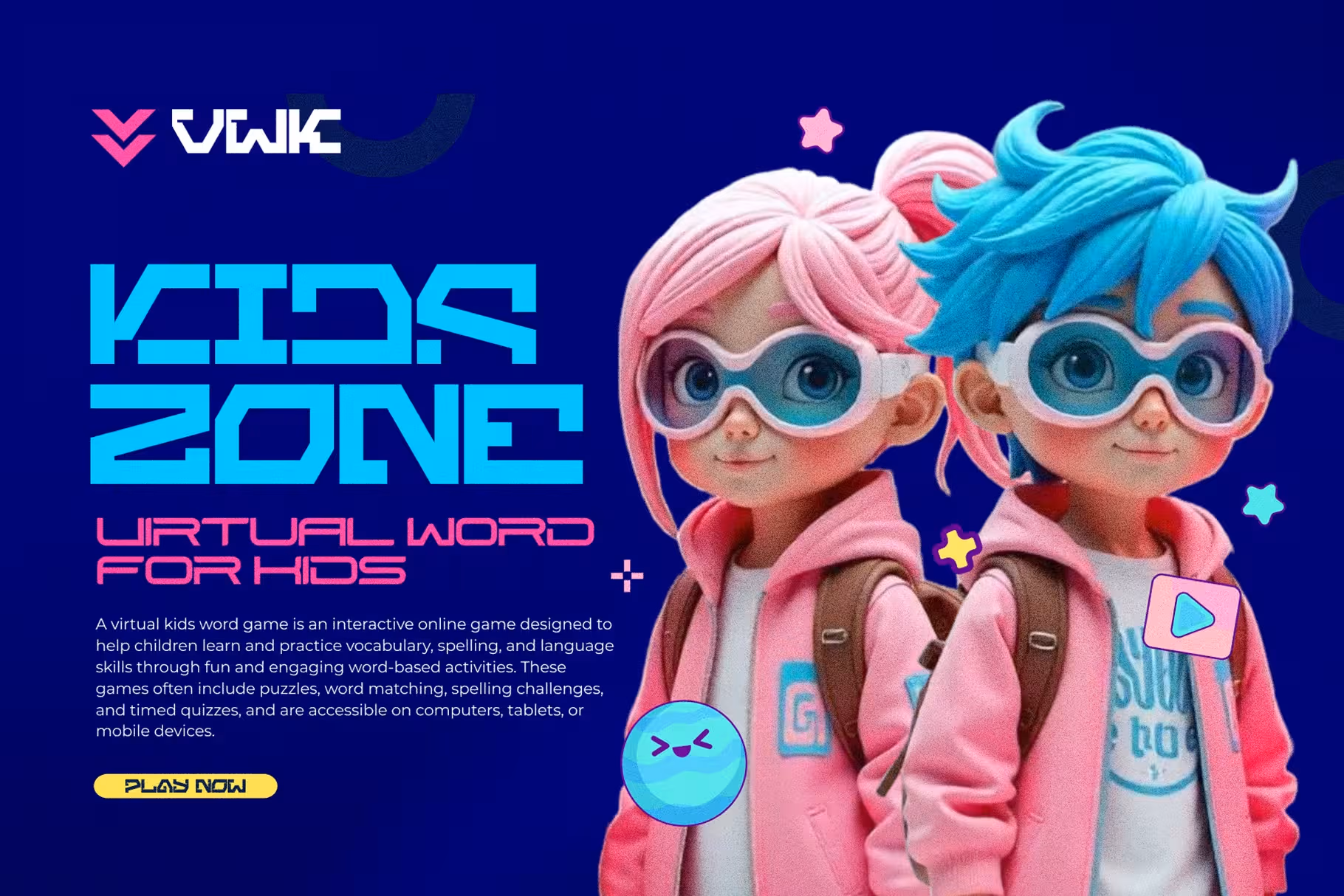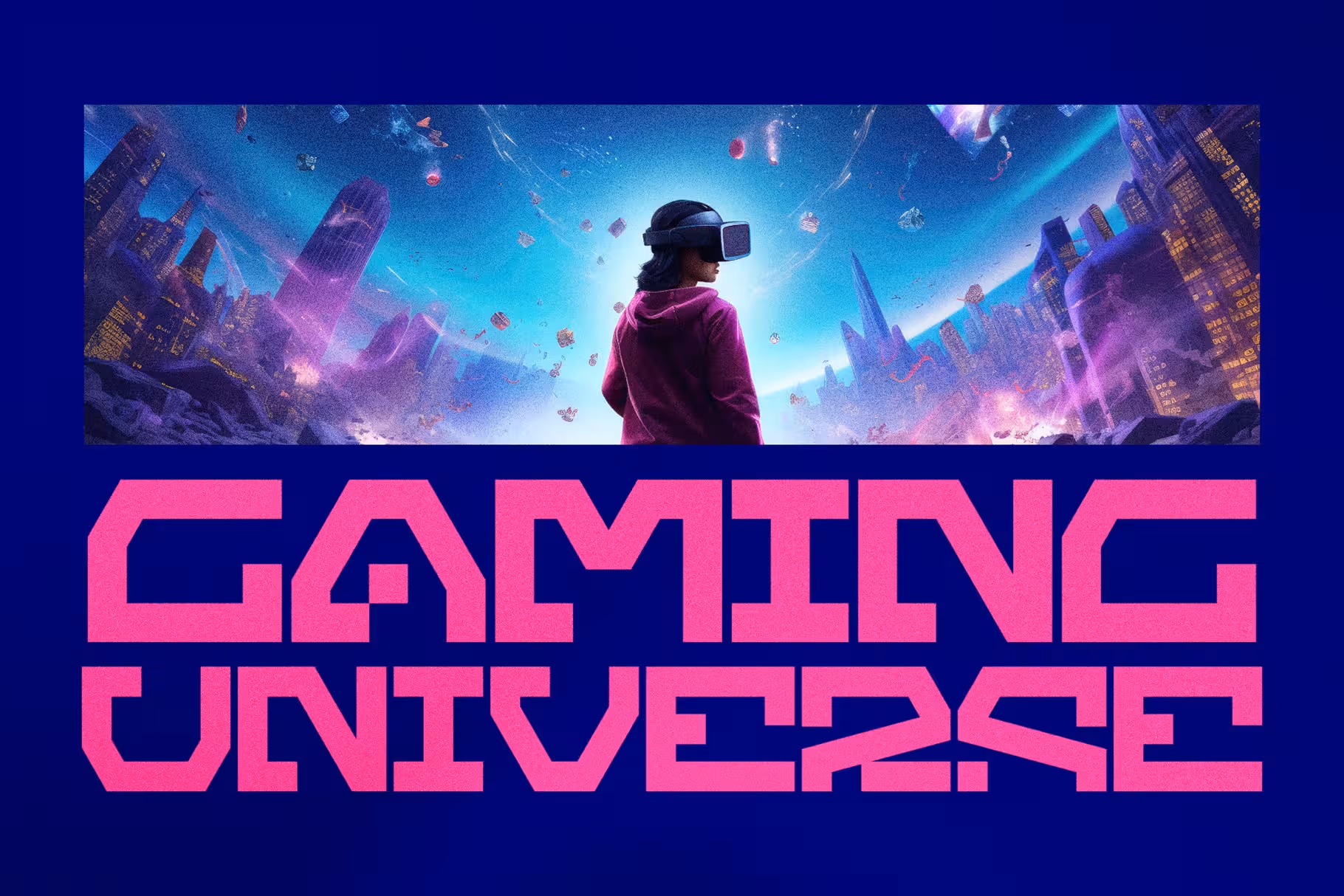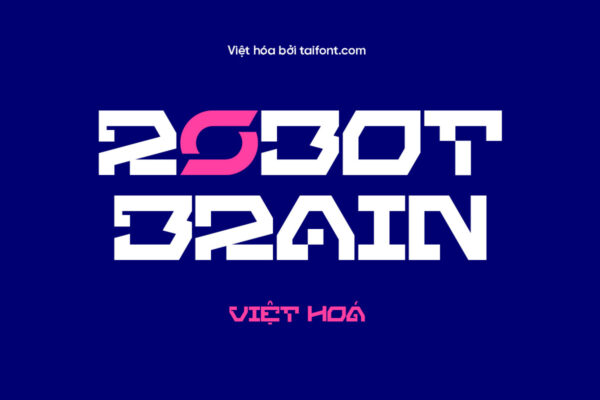
Giới thiệu về Font TF Robot Brain Việt hóa
TF Robot Brain Việt hóa là một font chữ trang trí độc đáo, nổi bật với thiết kế hiện đại, sắc nét và đầy tính công nghệ, gợi cảm giác về những mạch điện tử, mã code hoặc các yếu tố của trí tuệ nhân tạo. Font này toát lên phong thái tương lai, mạnh mẽ và đầy ấn tượng, lý tưởng để tạo điểm nhấn độc đáo và thu hút mọi ánh nhìn trong các thiết kế đòi hỏi sự tiên tiến và phong cách khoa học viễn tưởng.
Với đặc điểm thiết kế độc đáo, góc cạnh mạnh mẽ và khả năng gợi cảm xúc về công nghệ, Robot Brain là lựa chọn hoàn hảo cho các ấn phẩm trong lĩnh vực giải trí, công nghệ và tương lai:
- Thiết kế game: Hoàn hảo để sử dụng cho logo game, tiêu đề, hoặc các ấn phẩm quảng bá các tựa game khoa học viễn tưởng, game hành động, game chiến thuật hoặc game có chủ đề robot, AI. Font này giúp tạo không khí kịch tính, lôi cuốn và đầy thách thức, làm nổi bật tên game hoặc các tiêu đề quan trọng, khiến game thủ cảm thấy hào hứng và muốn khám phá.
- Công nghệ game: Lý tưởng để sử dụng trong các giao diện người dùng (UI) của game, màn hình tải game, hoặc các yếu tố đồ họa liên quan đến công nghệ, hệ thống AI trong game. Nét chữ sắc sảo của font sẽ làm tăng tính chân thực và độ “ngầu” cho trò chơi.
- Poster game: Phù hợp cho các poster quảng bá game, banner sự kiện E-sport, hoặc các ấn phẩm truyền thông liên quan đến công nghệ game. Font này giúp tạo không khí mạnh mẽ, đầy sức hút và gây tò mò cho người xem.
- Thiết kế nhận diện thương hiệu (công nghệ): Có thể dùng cho logo hoặc bộ nhận diện thương hiệu của các công ty, doanh nghiệp trong lĩnh vực công nghệ, robot, AI, hoặc các sản phẩm mang tính đột phá.
Với TF Robot Brain Việt hóa, bạn có thể dễ dàng thổi hồn công nghệ, sự độc đáo và cá tính vào các thiết kế, tạo ra những sản phẩm không chỉ đẹp mắt mà còn cực kỳ ấn tượng và có khả năng thu hút sự chú ý tối đa.